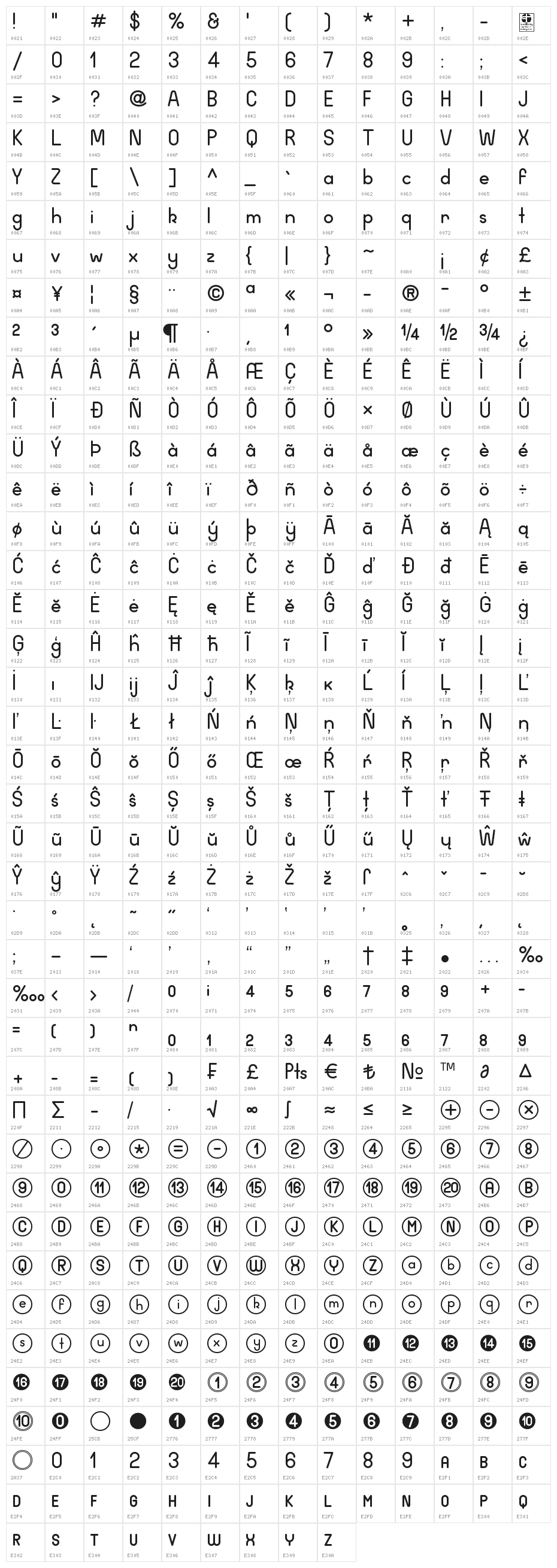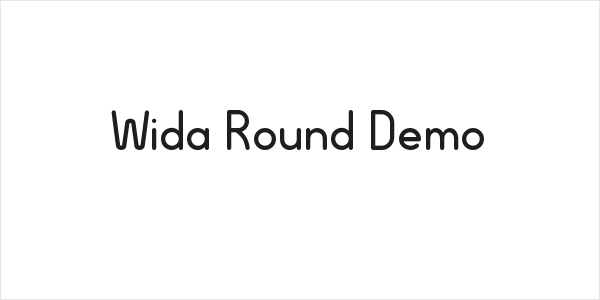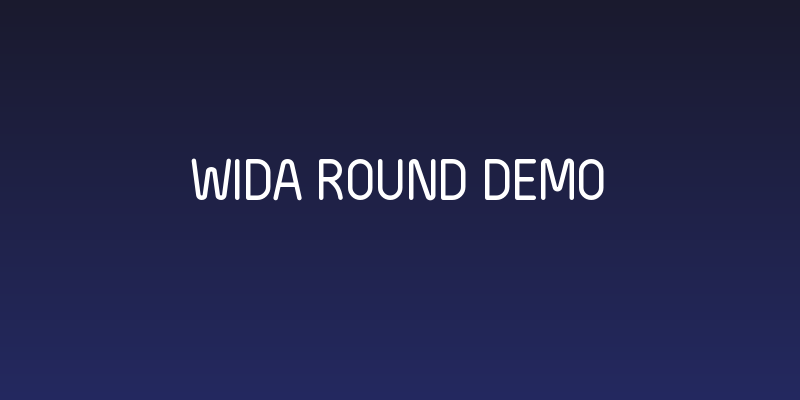
Wida Round Demo Font
| Progetti proposti | Ideal for branding, children's books, product packaging, and digital interfaces where a friendly and modern aesthetic is needed. |